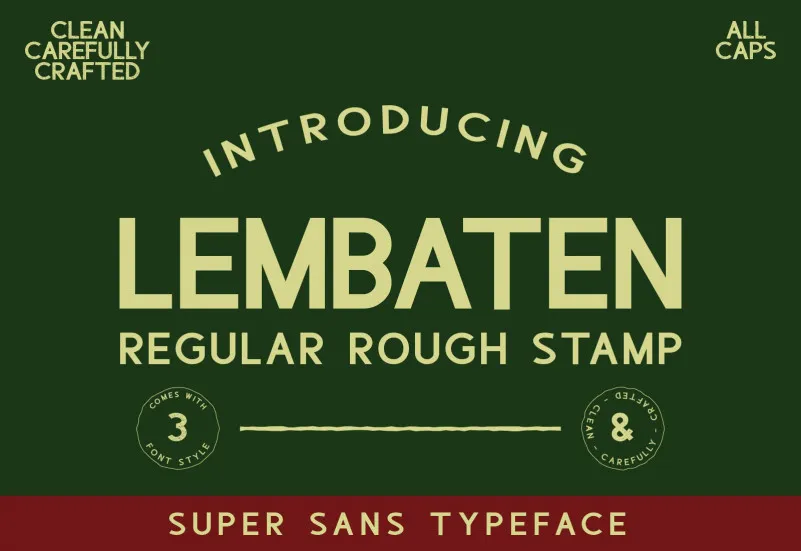
A Lembaten Font é uma nova adição à coleção das fuentes sans serif que traz simplicidade e elegância clássica. Inspirada nas anúncios e revistas de propaganda dos anos 90, esta fonte atende perfeitamente a um vasto número de projetos. Seu design minimalista permite uma fácil adaptação para diversas utilizações, tornando-a uma escolha versátil para designers que querem destacar seus trabalhos criativos. Lembaten é ideal tanto para textos informativos quanto para elementos gráficos visuais, oferecendo um toque único e moderno a qualquer projeto. Adicionar esta fonte à sua biblioteca de recursos gráficos pode transformá-lo em uma ferramenta poderosa para expressar sua personalidade visual de forma inovadora.